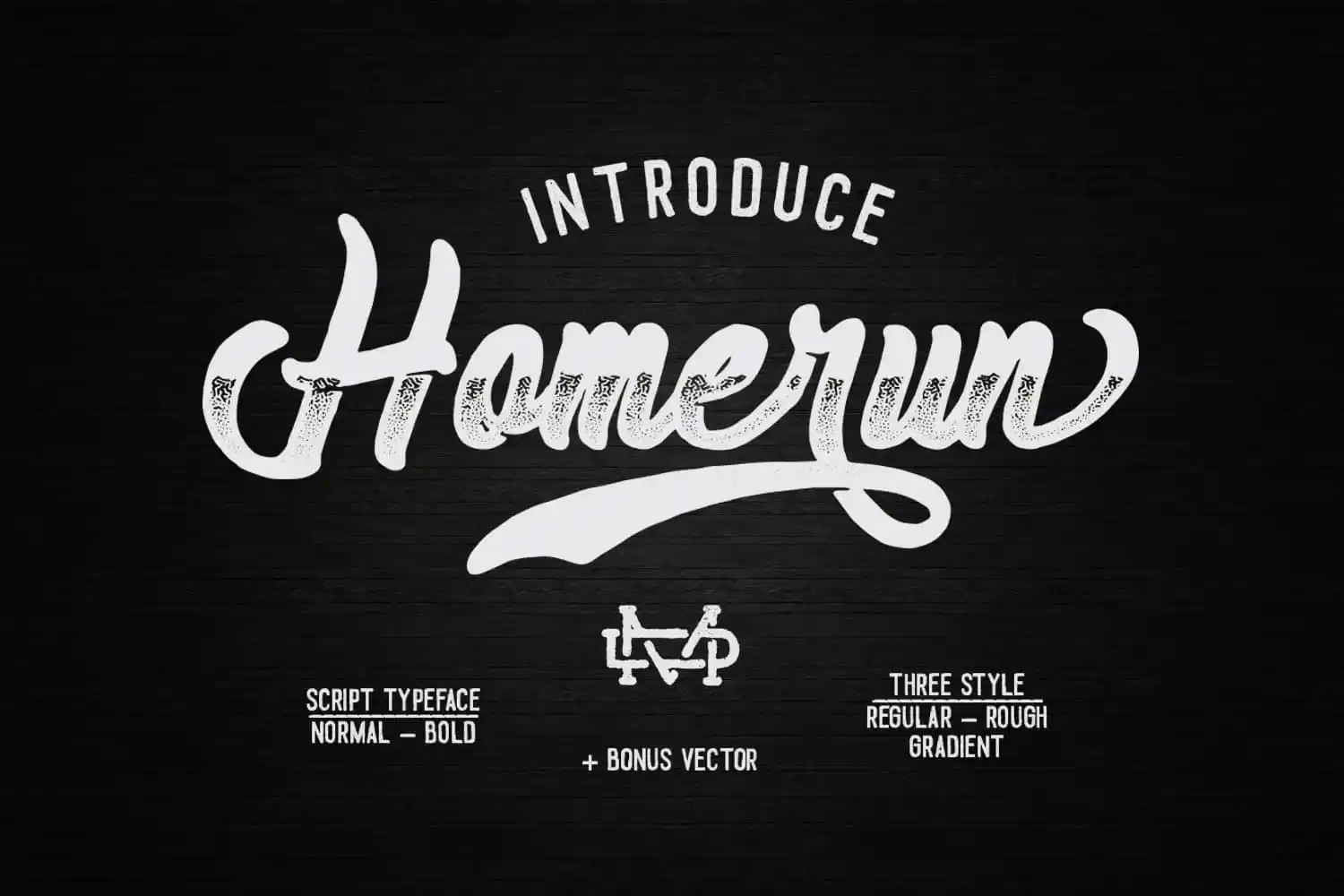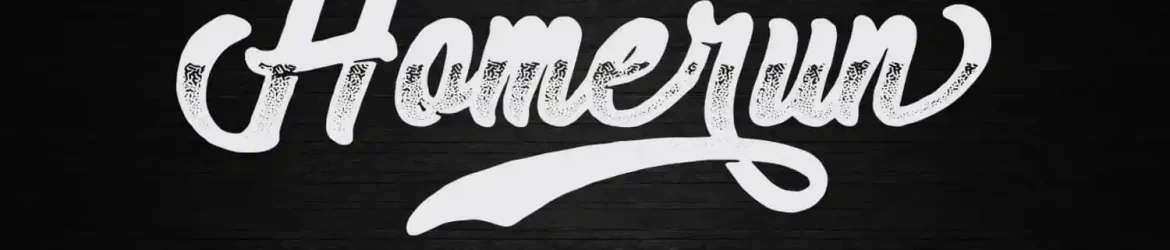
Homerun Script Font – Download Grátis
A Homerun Script Font é uma excelente escolha para quem deseja dar vida a designs de campanhas de moda, capas de livros ou até mesmo cartões de aniversário. Com três alternativas regulares, estampada e gradiente disponíveis, essa fonte oferece flexibilidade para adaptar seu design em um vasto conjunto de aplicativos, desde o design de outdoors até a criação de newsletters e cartelas de marcas. Suas linhas elegantes permitem que você personalize sua identidade visual ou crie materiais promocionais vibrantes. Perfeita para se destacar na era digital, essa fonte é uma ótima adição à sua coleção de recursos gráficos.